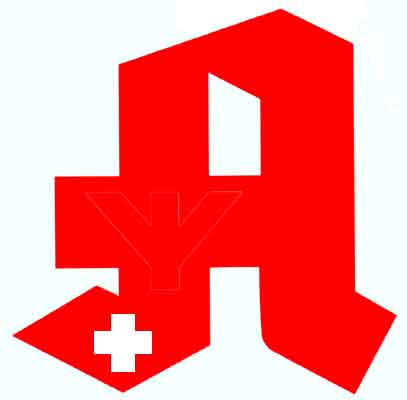
Schriftmuster Tannenberg
wir hatten an anderer stelle schonmal das apotheken-logo erwähnt, jetzt lese ich gerade bei wikipedia:
1929/30 siegte in einem Wettbewerb der Fa. Verunda das von der Bauhaus-Schule inspirierte „Drei-Löffel-Flasche“-Zeichen, das eine dreimal tägliche Einnahme eines flüssigen Arzneimittels symbolisiert. Nach fünf Jahren wurde es immerhin von rund einem Drittel aller Apotheken genutzt; es blieb jedoch wegen seines „schockierend modernen“ Stils umstritten. Das angeblich einzige erhaltene Drei-Löffel-Symbol wird im Deutschen Apotheken-Museum im Heidelberger Schloss gezeigt.
und weiter:
Ein neuerlicher Wettbewerb 1936 wurde unter der Ägide des seit 1933 amtierenden „Reichsapothekenführers“ Albert Schmierer vom roten A gewonnen; doch das ursprünglich im Entwurf vorgesehene weiße Kreuz wurde wegen der Ähnlichkeit zum Schweizerkreuz verworfen und durch die „zeitgemäße“ Lebens-Rune ersetzt.[7] Das neue Apotheken-A wurde 1937 flächendeckend eingeführt. Schnell hatte dieses Zeichen einen sehr hohen Bekanntheitsgrad erreicht.
sieht man mal von der lebenrune ab, welche die nazis später in das logo gesetzt haben — wurde das logo geändert weil das andere nicht einprägsam und eventuell unverständlich war, der neu-entwurf jedoch plakativer ist? oder wurde es geändert weil die nazis das bauhaus verflucht haben und lieber ihre gebrochenen gotischen schriften sehen wollten?
… besonders bei Plakatgestaltern aus der 3. Reihe, die sich ihnen Lebensunterhalt mit Propagandaplakaten finanzieren wollten, daher wurde die Schriftart eben auch öfter, wenn auch nicht unbedingt vorrangig zu diesem Zweck verwendet …
Warum vor allem aus der 3. Reihe?
An dieser ausgeklügelten Propagandamaschinerie waren ebenso die der 1. Reihe beteiligt.
Auch wie bei Schauspielern, Sängern, Dirigenten, Sportlern etc. die Besten, wenn nicht emigriert, so dann als Mitläufer für oder unter den Nazis arbeiteten.
Mit der 3. Reihe gaben die Nazis sich nicht zufrieden.
zu den »Reihen« kann man in Renners »Kulturbolschewismus« nachlesen – da geht es zwar eher um Künstler und Architektur aber das Buch passt hier auch ganz gut rein.
einen Grafiker, den ich in die erste Reihe setzen würde wäre Ludwig Hohlwein – aber wirklich fortschrittlich fand ich den jetzt in den 30er Jahren nicht mehr – der hat perfekt das Regime bedient und es ist wohl auch aktuell der einzige, der mir gerade einfällt.
Wenn wir die ganze Nazi-Propaganda-Maschinerie nun nur den Mittelmäßigen oder Drittklassigen in die Schuhe schieben, dann sind wir ja fein raus.
war das eine Antwort auf mein Posting  oder eine Ergänzung zu deinem weiter oben ?
Zu meinem Beitrag würde es nicht passen.
Es ist ein Trugschluss, sich einzureden, dass unter den Nazis nicht auch die Besten tätig waren.
Nach Jahrzehnten stellt sich dann bei so mancher „moralischer Instanz“ heraus, auch er oder sie setzte sein Talent für die Nazis ein.
Es gibt genügend Plakate, Skulpturen etc. die unter und für die Nazis geschaffen wurden. Von talentierten Künstlern oder Gestaltern.
Sie waren vor den Nazis nicht gefeit. (Siehe auch den Beitrag „Als die Künstler in den Krieg zogen“ weiter vorne!)
Auch Talent und Begabung boten keinen Schutz oder garantierten für weise Voraussicht.
Wenn hier davon geredet wird, dass es ja meist Gestalter der 3. Reihe waren, würde ich das als Versuch des Relativierens bezeichnen.
dein Beitrag als die Künstler in den Krieg zogen bezieht sich aber auf den 1. Weltkrieg
die Nazis hatten eine ganz eigene Einstellung zur Kunst – ich hab da vor einiger Zeit einen Link gepostet und auch Renners Kulturbolschewismus ist da lesenswert
@CLMNZ: Ist mir klar, hatten wir damals auch besprochen. Es sollte ein Beispiel sein, dass auch die guten Künstler sich verblenden lassen. (Gehört nicht zum folgenden  Beitrag, sondern nur zum Beitrag von CLMZ)
Dieses Plakat entstand in den 20er-Jahren des vorigen Jahrhunderts. Jedenfalls vor 1927.
Nachdem zu dieser Zeit oft Plakatmaler für diese Arbeiten zuständig waren, gingen von dieser Berufsgruppe sicherlich Impulse auch für die Schrifgestaltung aus.
Bis zur Realsierung der fertigen Druckschriften vergingen, der damaligen Technik geschuldet, ein paar Jahre.
das mit der 3.Reihe war nur eine Anspielung (rein rhetorisch) auf die Schriftgestalter aus der 3. Reihe, welche angeblich die Schriften gebaut hatten.
zu "zu 1" Natürlich erkenne ich an, dass es ähnliche Schriften schon vor 1933 gab, aber so richtig populär, oder meinetwegen modern waren sie erst so knapp um 1933. Ähnliches swehe ich ja auch jetzt bei derzeit recht modernen Schriftebn, bei denen einige schon vor längerer Zeit entworfen sind, sich aber zunächst kaum absetztm ließen - weil vor der Zeit.
Ich bin hier nur eingestiegen, weil mir die Thesen fragwürdig erschienen, die Gattung hätte so gar nichts mit den Nazis zu tun, sei völlig unabhängig  von der gesellschaftspolitischen Entwicklung entstanden/im Handumdrehen populär geworden …
Sagte halt nur niemand …